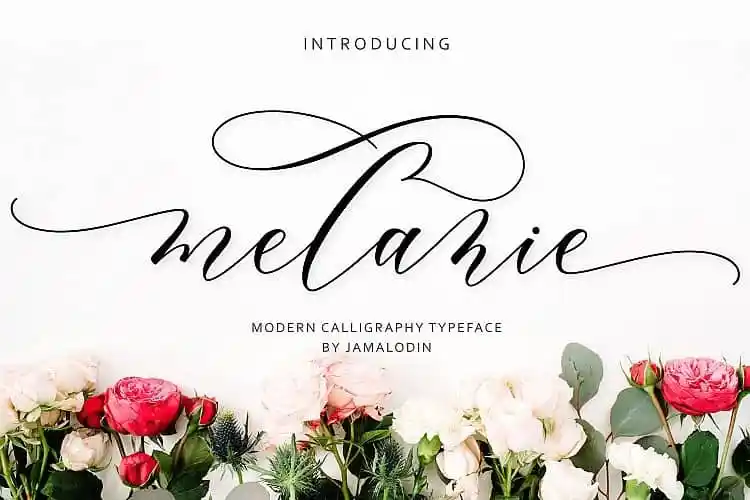
Melanie Calligraphy Font – Download Grátis
Melanie Calligraphy Font é uma fonte script moderna que incorpora elementos de escrita a mão com caracteres decorativos, projetada para combinar naturalmente com scripts informais, românticos, provocantes e suaves. Suas formas clean e elegantes permitem que você use Melanie em uma ampla variedade de projetos, desde cartões de convite até posteres, nomes de cartão de visita ou bordados, mensagens personalizadas para blogs, estilos de marca, logotipos, roupas fashion e materiais de escrita. Esta fonte perfeita para vários usos é uma excelente escolha para designers em busca de um estilo sofisticado que também tem seu charme natural a mais. Sempre pronto para dar um toque especial aos seus trabalhos gráficos.